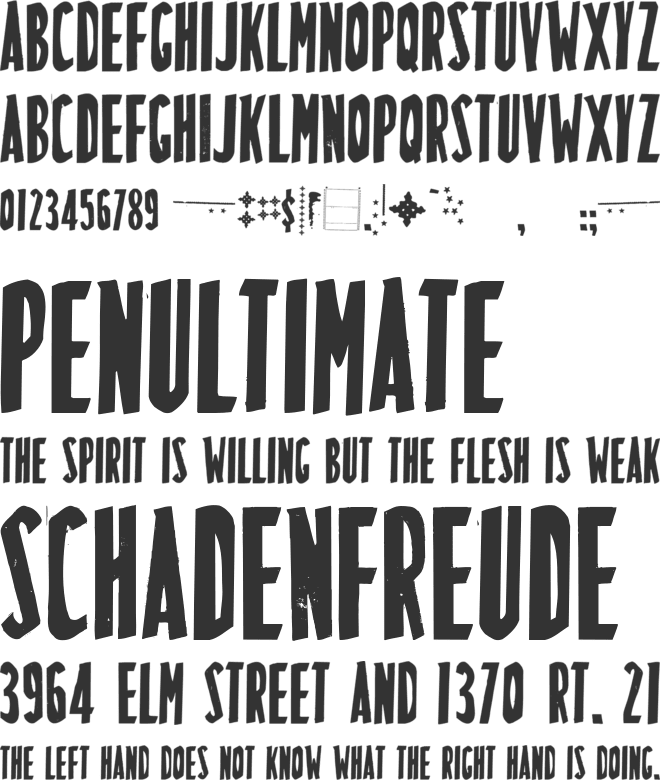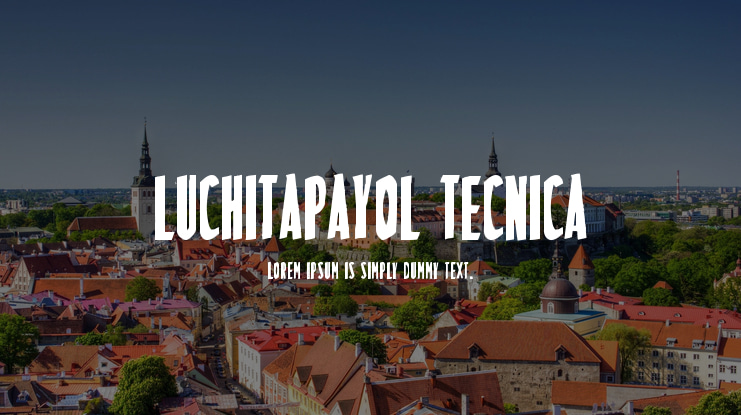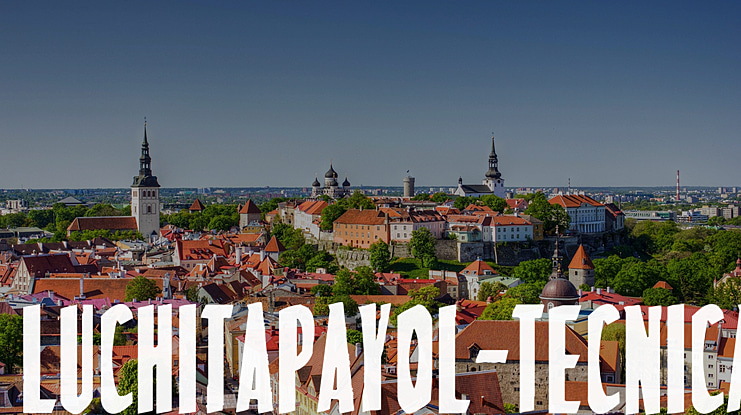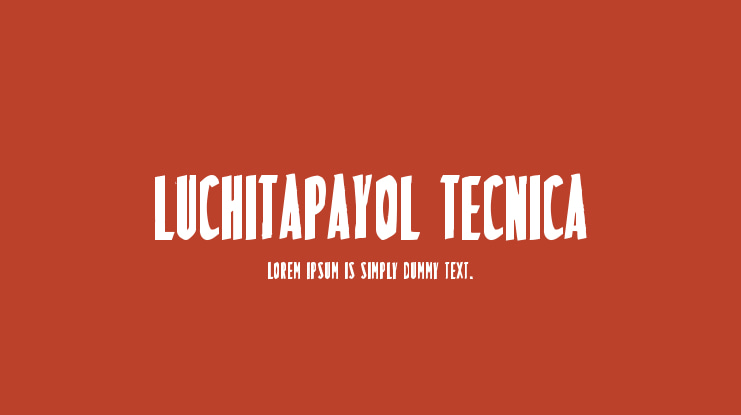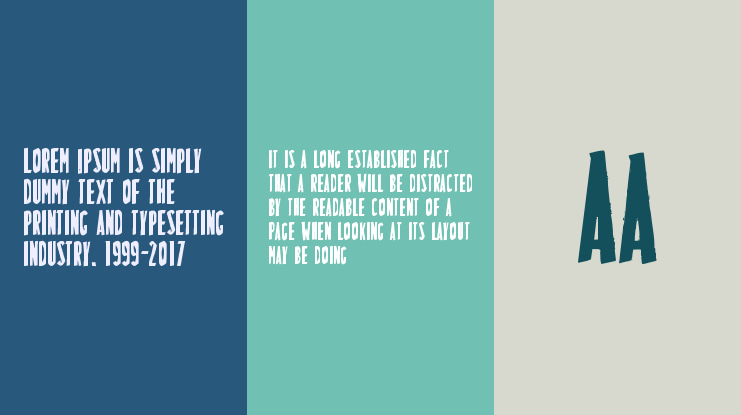
LuchitaPayol Tecnica Font
Dise\226ada en Hula+Hula por Quique Ollervides a finales del a\226o 2000 y principios del 2001. Basada en los tipos m\227viles en linoleo de la Imprenta Payol.